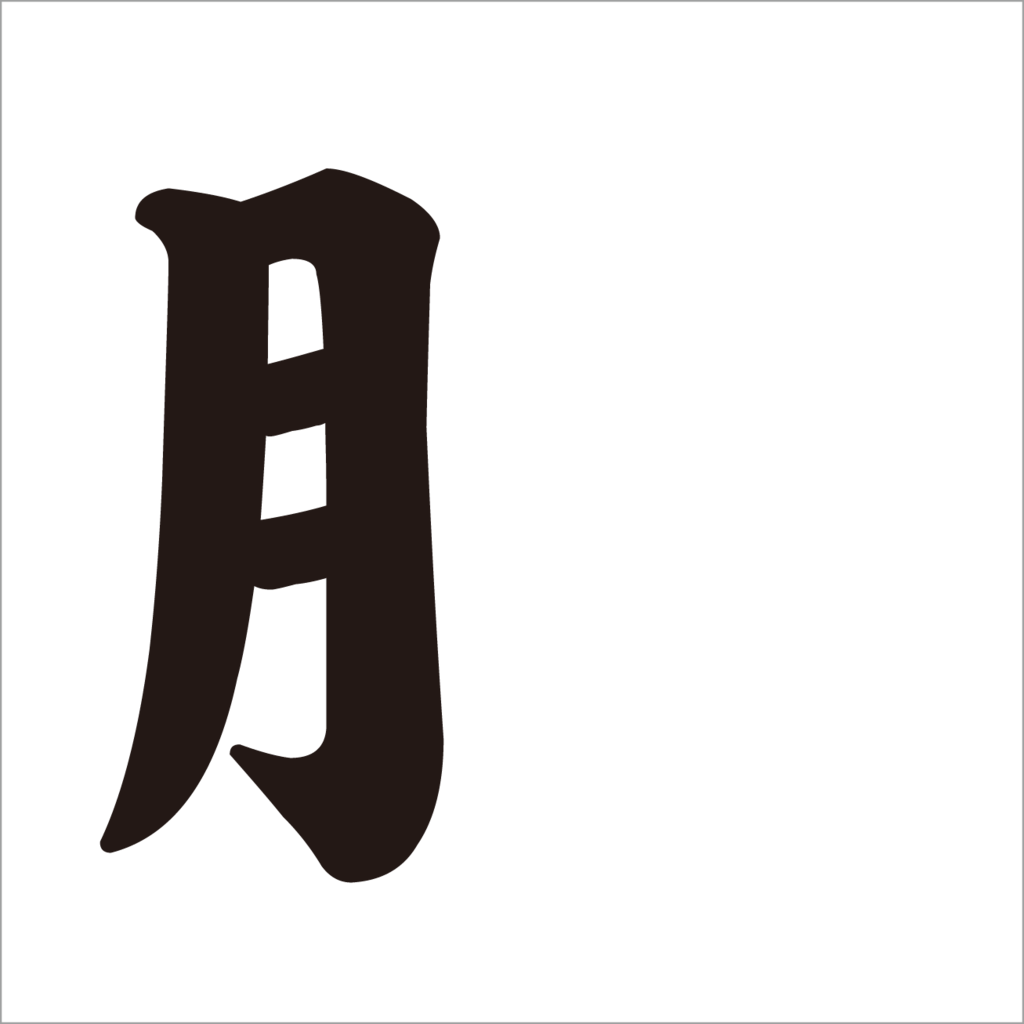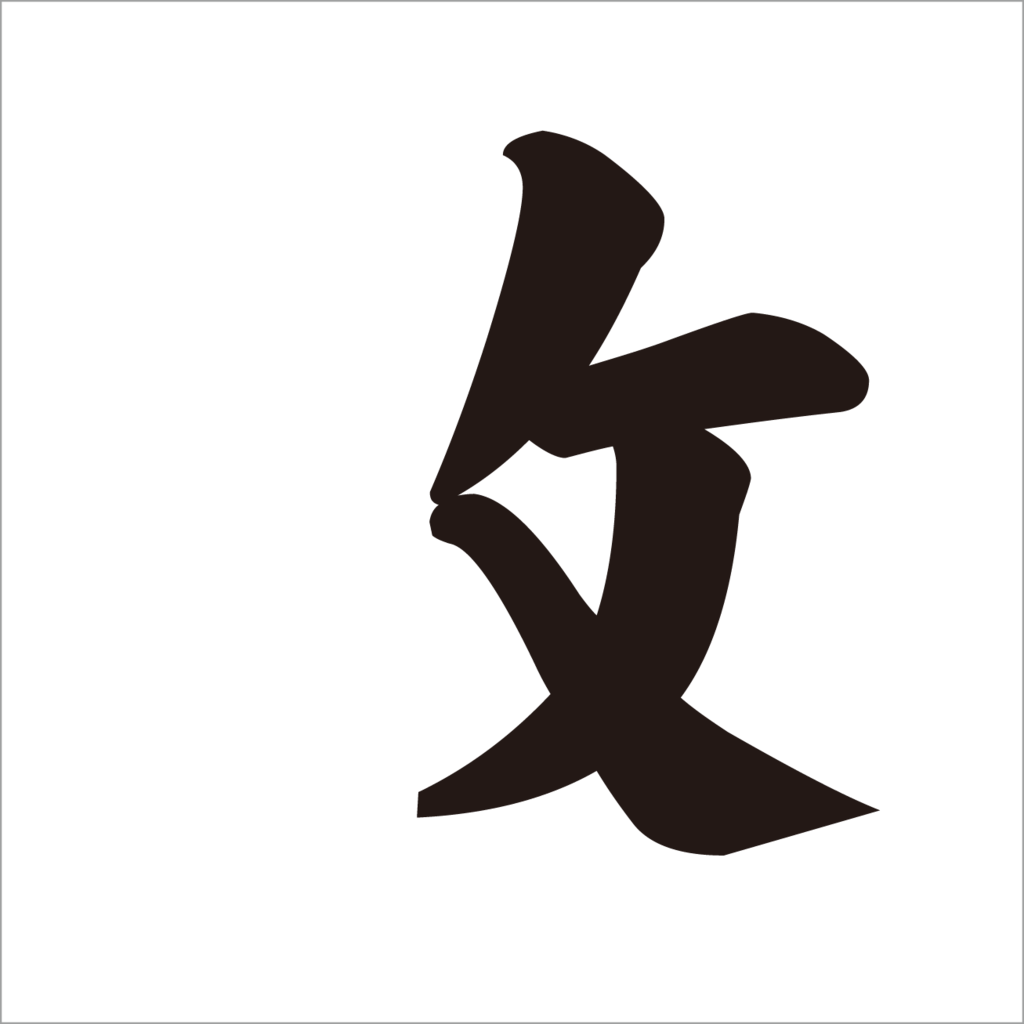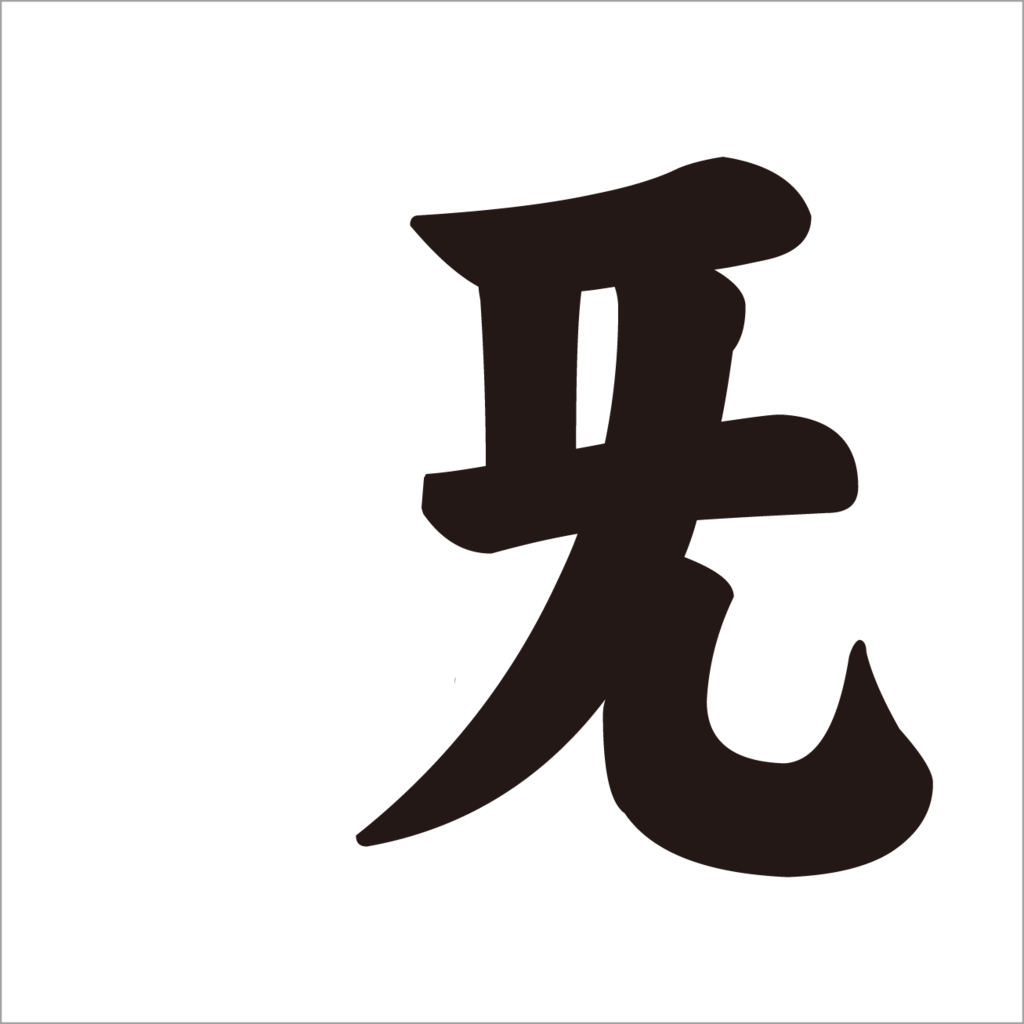
天皇陛下のお気持ち表明フォント・ダイナフォントの超極太楷書体で作成した「部首」見本
誰が買うのか購買層がよくわからないが…漢字部首コレクションが楷書体なので、漢字部首コレクションに採用された部首10種類「きへん」「まだれ」「つきへん」「えんにょう」「しめすへん」「のぶん」「はつがしら」「すでのつくり」「おいかんむり」「たけかんむり」をNHKで放送の天皇陛下のお気持ち表明で話題になった超極太楷書体で作ってみた。
きへん
天皇陛下のお気持ち表明フォント・ダイナフォントの超極太楷書体で部首・きへん。
まだれ
天皇陛下のお気持ち表明フォント・ダイナフォントの超極太楷書体で部首・まだれ。
つきへん
天皇陛下のお気持ち表明フォント・ダイナフォントの超極太楷書体で部首・つきへん。
えんにょう
天皇陛下のお気持ち表明フォント・ダイナフォントの超極太楷書体で部首・えんにょう。
しめすへん
天皇陛下のお気持ち表明フォント・ダイナフォントの超極太楷書体で部首・しめすへん。
のぶん
天皇陛下のお気持ち表明フォント・ダイナフォントの超極太楷書体で部首・のぶん。
はつがしら
天皇陛下のお気持ち表明フォント・ダイナフォントの超極太楷書体で部首・はつがしら。
すでのつくり
天皇陛下のお気持ち表明フォント・ダイナフォントの超極太楷書体で部首・すでのつくり。
おいかんむり
天皇陛下のお気持ち表明フォント・ダイナフォントの超極太楷書体で部首・おいかんむり。
たけかんむり
天皇陛下のお気持ち表明フォント・ダイナフォントの超極太楷書体で部首・たけかんむり。
大見出し用楷書体・超極太楷書体
大見出し用の楷書体。オーソドックスな構成と筆法で書かれており、他の楷書体がもつ灰汁の強さを極力押さえられ、汎用性のある楷書体として使いやすいようデザインされている。